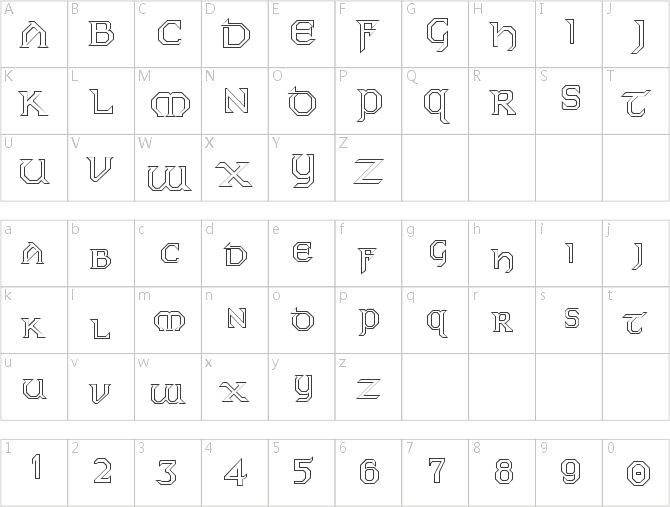
FZ JAZZY 31 HOLLOW 詳情頁(yè)
FZ JAZZY 31 HOLLOW字體字庫(kù)是一款讓人賞心悅目、百看不厭的英文字體,適合各類(lèi)廣告和產(chǎn)品包裝設(shè)計(jì)應(yīng)用,字體大小0.06MB,格式為ttf字體,上傳用戶是那是不變的,作者/版權(quán)方為未知